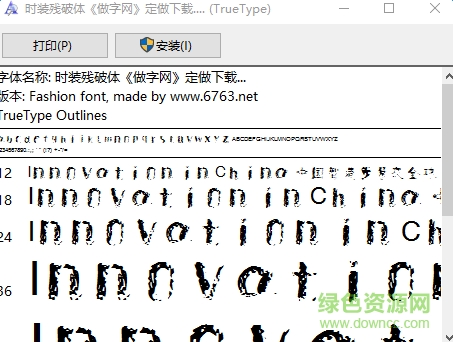
時(shí)裝殘破體
時(shí)裝殘破體時(shí)裝字體中的一款很有個(gè)性的電腦藝術(shù)字體,正是因?yàn)檫@款字體比較有個(gè)性,所以也是深受廣大朋友們的喜歡,所以小編已經(jīng)將這款字體打包好了,歡迎有需要的朋友來(lái)綠色資源網(wǎng)下載。
小編點(diǎn)評(píng)
時(shí)裝殘破體就像它的名字所說(shuō)那樣是殘破的,但是寫(xiě)出來(lái)的字效果很不錯(cuò),也很好看,有一種很縹緲的感覺(jué),喜歡的朋友就來(lái)綠色資源網(wǎng)下載吧。